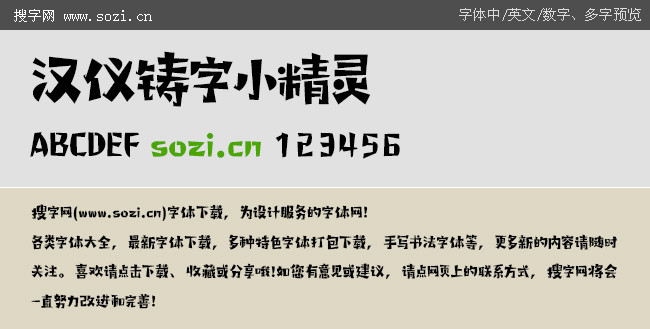
漢儀鑄字小精靈
搜字網(wǎng)給大家提供一款漢儀鑄字小精靈中文字體下載,漢儀鑄字小精靈字體字形變化多樣,調(diào)皮活潑、萌趣可愛,適用于畫冊設(shè)計(jì)、海報(bào)設(shè)計(jì)、包裝設(shè)計(jì)等場合使用。(本字體為個(gè)人非商用版,如需要商用請聯(lián)系漢儀公司購買版權(quán))